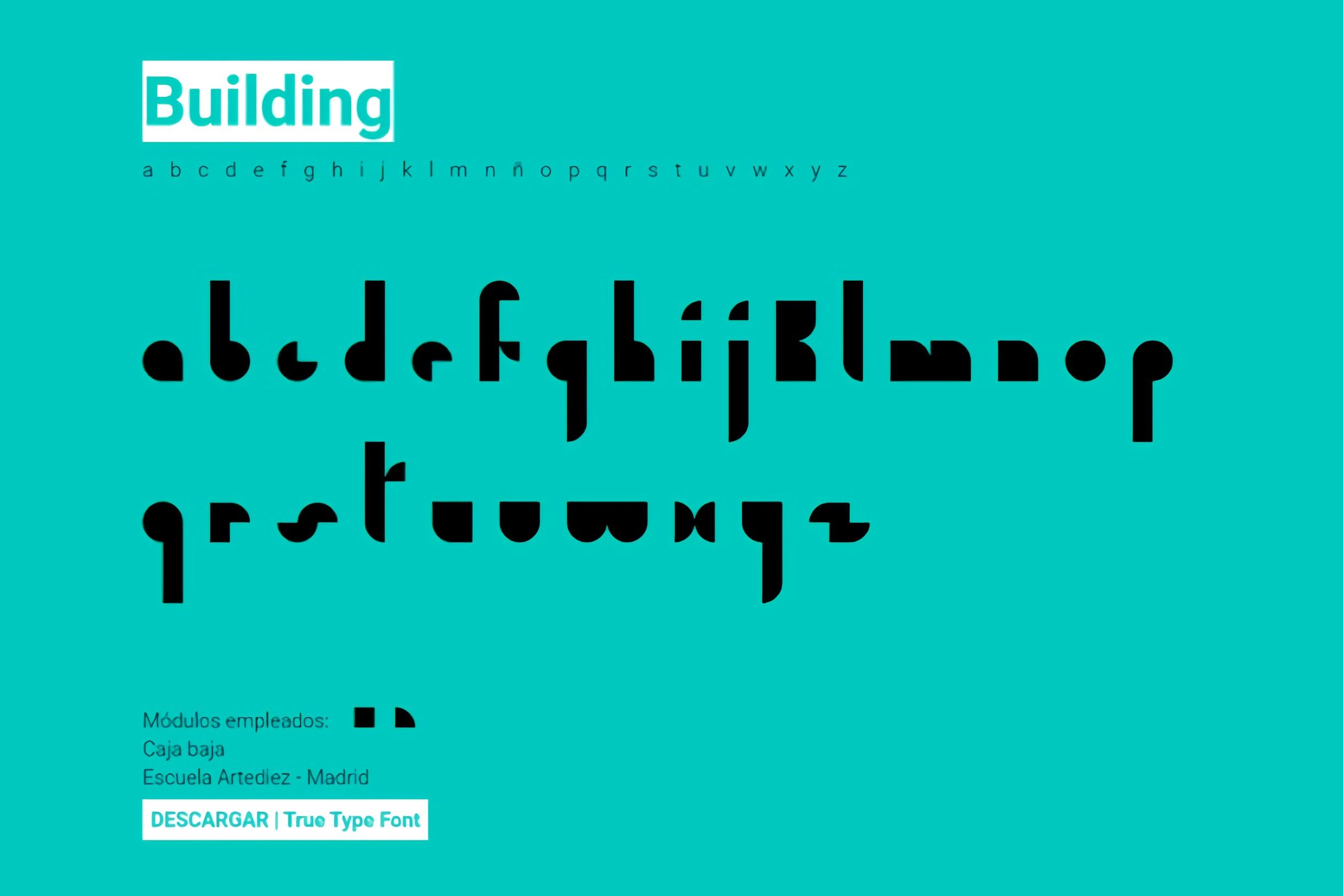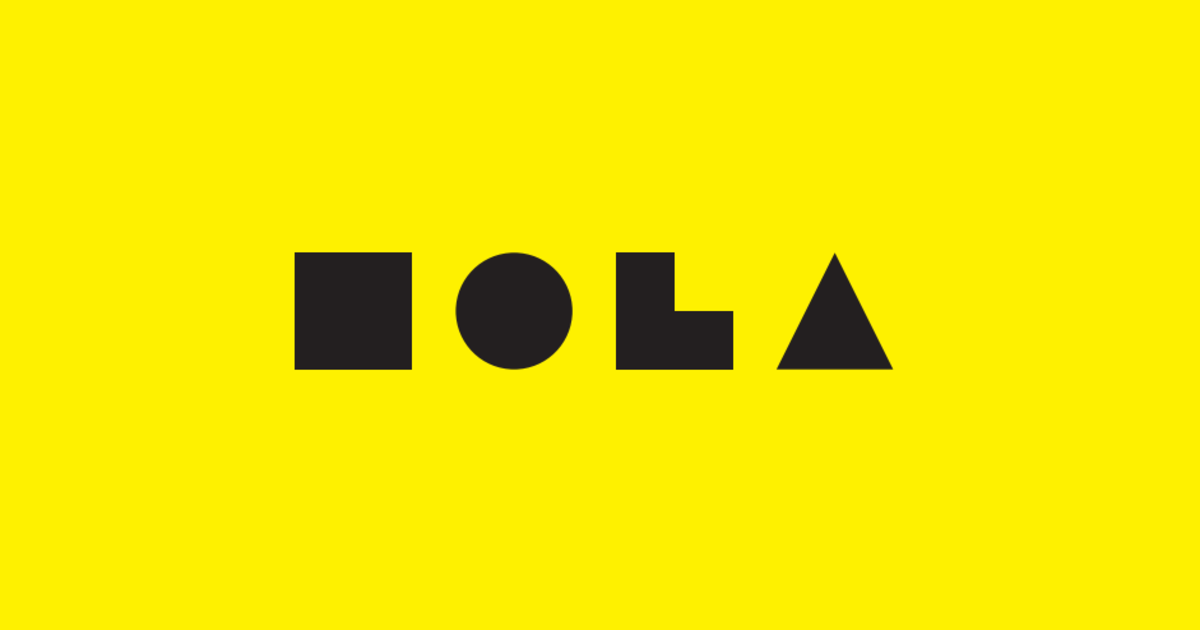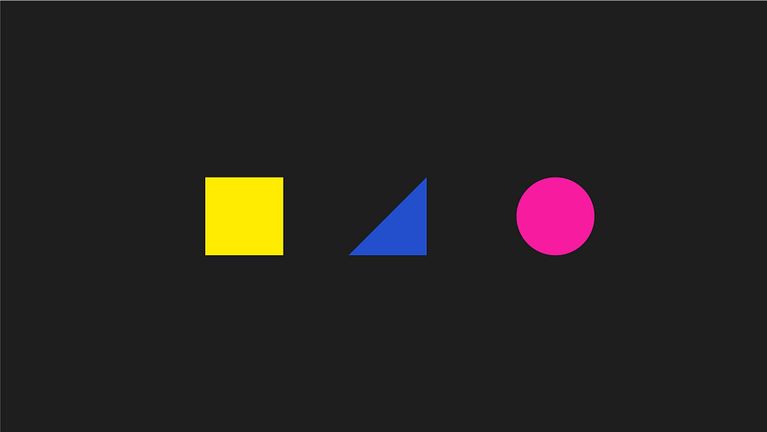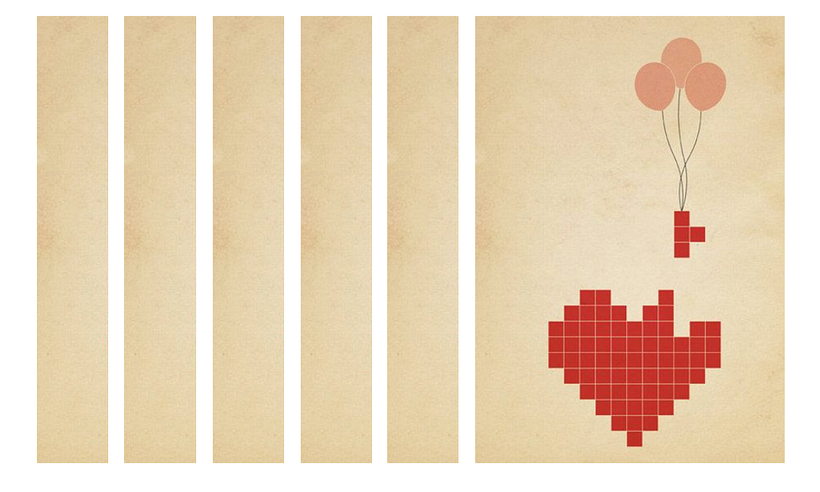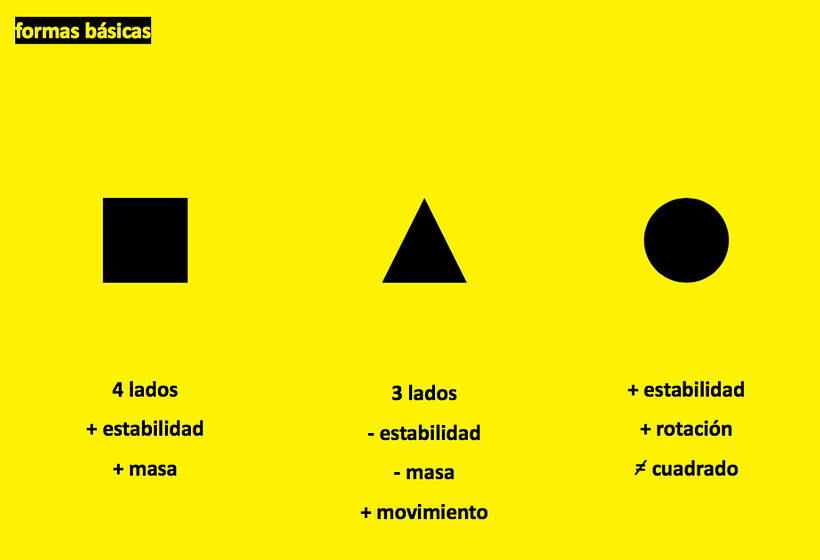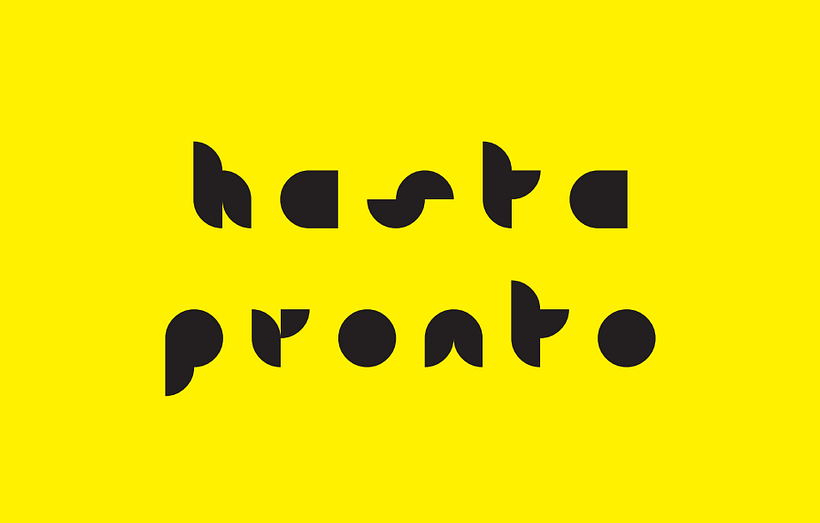
Introducción a la tipografía modular
Descubre las características y posibilidades de esta alternativa tipográfica
Diseño modular
Para entender cómo funciona la tipografía modular, es importante empezar por este concepto clave. El diseño modular es aquel que está basado en la modulación reticular de espacios que permiten optimizar el tiempo a la hora de llevar a cabo cualquier construcción, tarea o proyecto. Dado a que pueden ser transportados, desarmados y reorganizados, permiten el uso de múltiples funciones y reutilizarse para generar un nuevo uso diferente con el fin que fueron fabricados.
Formas básicas
Este sistema se caracteriza por:
- Permitir la partición o fragmentación de las funciones en módulos para ser reutilizados.
- Tener la capacidad de definir la función y orientación de cada módulo.
- Aportar y estar dispuesto a facilidades de cambios, flexibilidad, comprensión y sistemas estandarizados.
Tipografía modular
La tipografía modular consiste en proyectar y construir un alfabeto a partir de módulos y formas preconstruidas. Puede ser que el primer paso para introducirse en el mundo de la tipografía sea precisamente la tipografía modular.
Se trata de experimentar con la construcción de la letra partiendo de la modulación y las formas básicas, esto nos ofrece un mundo de posibilidades de formas y color para crear sistemas tipográficos complejos o simples donde la unión de los caracteres y los íconos está presente.
Formas básicas
El cerebro humano establece significados, identifica el contorno exterior de las figuras, al igual que lo hace con todo tipo de formas. Existen dos categorías generales de figura que tienen un efecto en el mensaje, cada una con sus características formales y comunicativas que son la figura geométrica y figura orgánica. En el caso que nos ocupa, consideraremos únicamente la figura geométrica, tratando su contorno regularizado, sus medidas exteriores similares, ángulos y borde definido.
Hay tres tipos esenciales de forma geométrica:
- El círculo
- El polígono
- La línea
Entre los polígonos más sencillos podemos encontrar el cuadrado y el triángulo, de cuatro y tres lados respectivamente. El cuadrado es más estable y presenta mayor masa; el triángulo es el polígono menos estable e introduce un gran movimiento óptico alrededor de su contorno. En cuanto al círculo, es casi tan estable como el cuadrado, aunque su curva continua sugiere rotación. Su principal cualidad, la curva, es completamente opuesta al cuadrado.
Alfabetos modulares
Para llegar a configurar un alfabeto modular, es necesario primeramente generar un sistema gráfico modular, en el cual una serie de formas geométricas se combinan para la creación de unidades mayores. Es decir, estas unidades mayores serán las letras completas que conformen un alfabeto.
Es necesario partir de las formas geométricas y un sistema para poder diseñar las letras y poder utilizarlas en su conjunto. Esto dará como resultado una idea de partida experimental que puede ser utilizada como herramienta gráfica para hacer composiciones tipográficas y modulares muy variadas.
Building TTF, Mercedes Grande
Según sean las figuras que integran los módulos, el diseñador establecerá su criterio propio y analítico ligado a la estructura y características de la tipografía modular que pretenda crear. Por tanto, hay que tener en cuenta aspectos como:
- La adecuada elección de las formas y las posibilidades que ofrecen.
- Experimentar en la construcción modular con tipos de caja alta y caja baja que componen el alfabeto.
- Tomar como referencia una letra inicial para desarrollar las restantes.
- Establecer un cuerpo medio de los caracteres, así como tener en cuenta la línea de base, la línea media, la línea de ascendentes y descendentes y la línea de las mayúsculas.